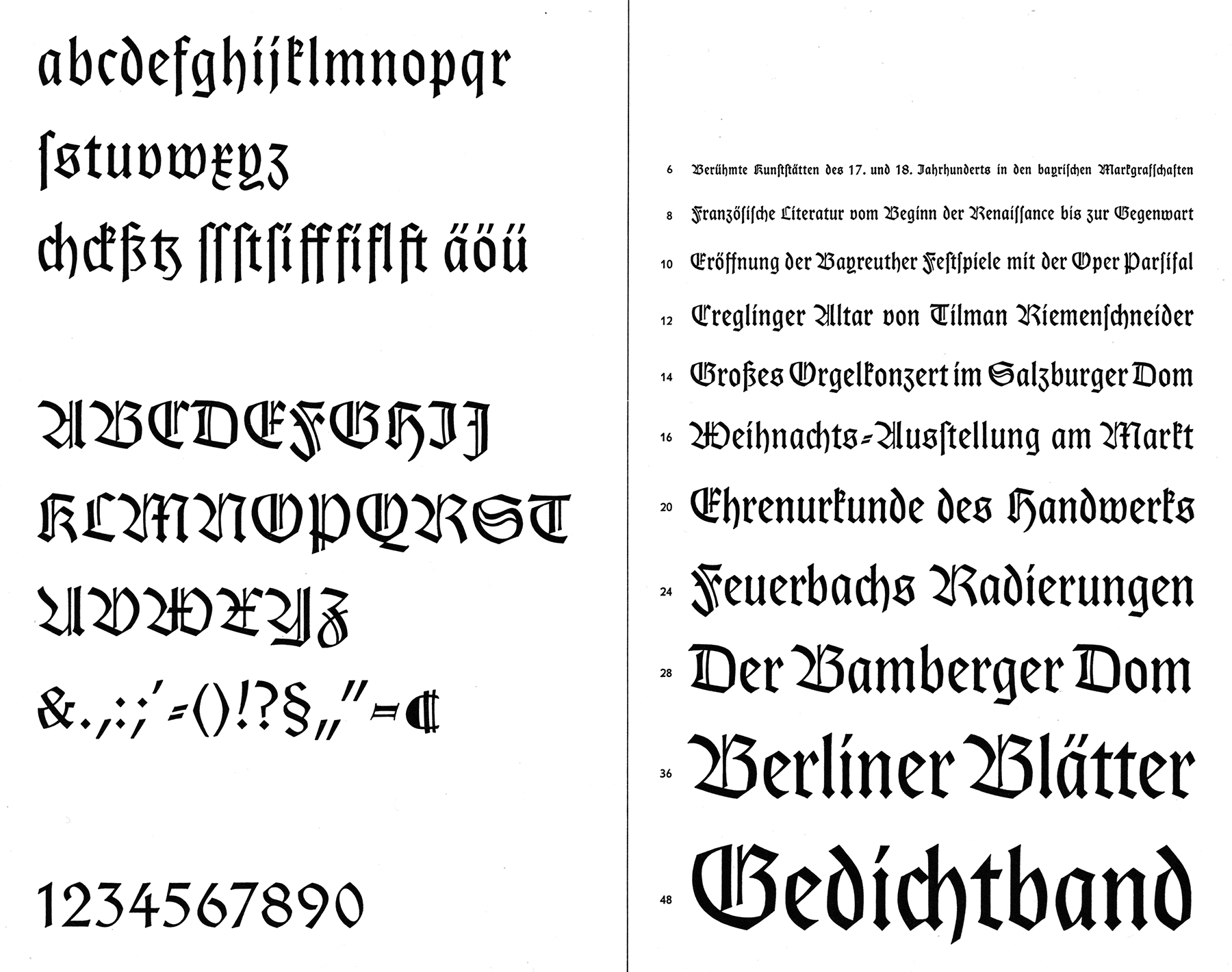
Die Hölderlin von Eugen Weiß erschien 1937 bei der Schriftgießerei Ludwig & Mayer. Bei der Schriftguß KG war die Schrift auch als Walhalla verfügbar.
Eine Digitalisierung gibt es als Hoelderlin von RMU Fonts.
Foundry: Ludwig & Mayer
erschienen: 1937
Formprinzip: Gebrochene Schrift